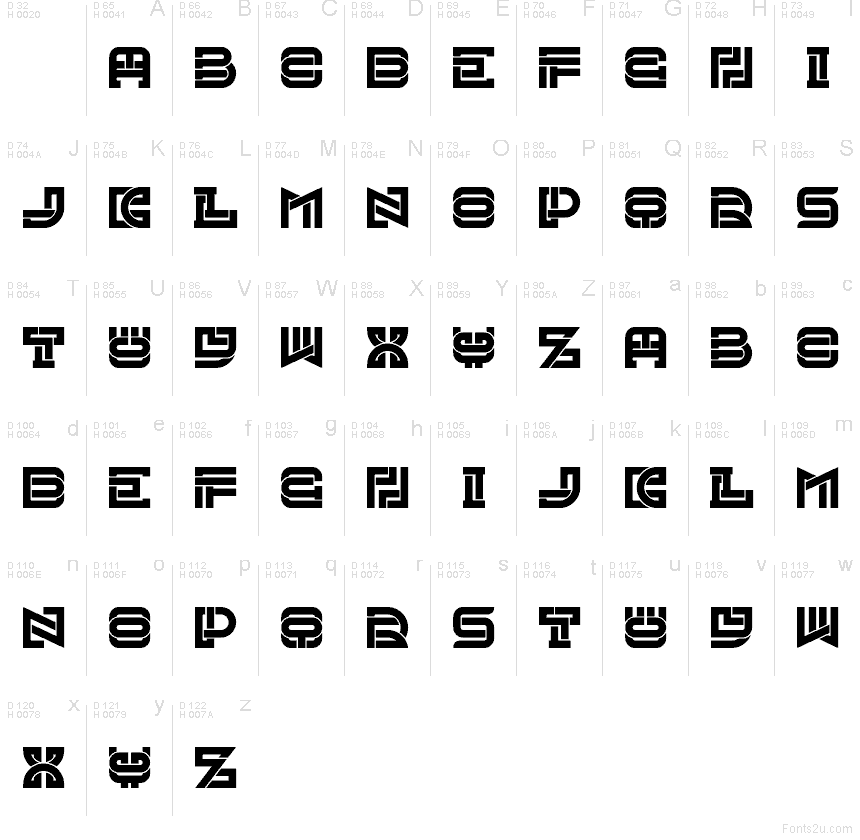
Museum Extravagant Regular
Museum Extravagant von Vladimir Nikolic ist eine kostenlose, futuristische Display-Schrift mit einem eleganten, modularen Rhythmus. Die Buchstaben bestehen aus kräftigen geometrischen Strichen, rechtwinkligen Ecken und abgerundeten, rechteckigen Schleifen. Dies verleiht dem Alphabet den Look einer Retro-Beschilderung aus einem Science-Fiction-Museum, bei der Wiederholung und Symmetrie das visuelle Gesamtbild prägen.
Dieser Look eignet sich hervorragend für Plakattitel, Albumcover, Ausstellungsdesigns, Markenauftritte und Titelkarten, bei denen die Buchstabenformen die Stimmung ganz von allein tragen. Als kostenlose Schrift eignet sie sich ideal für kurze Überschriften und Logo-Entwürfe, besonders wenn ein kompakter Wortmarken-Stil mit fließenden, ineinandergreifenden Formen gewünscht ist.
„Museum“ ist in den Varianten Regular, Hollow und Book erhältlich.